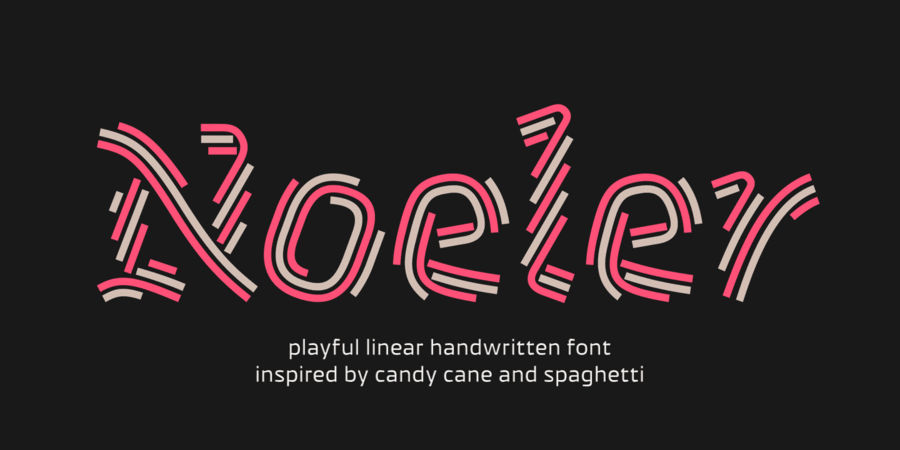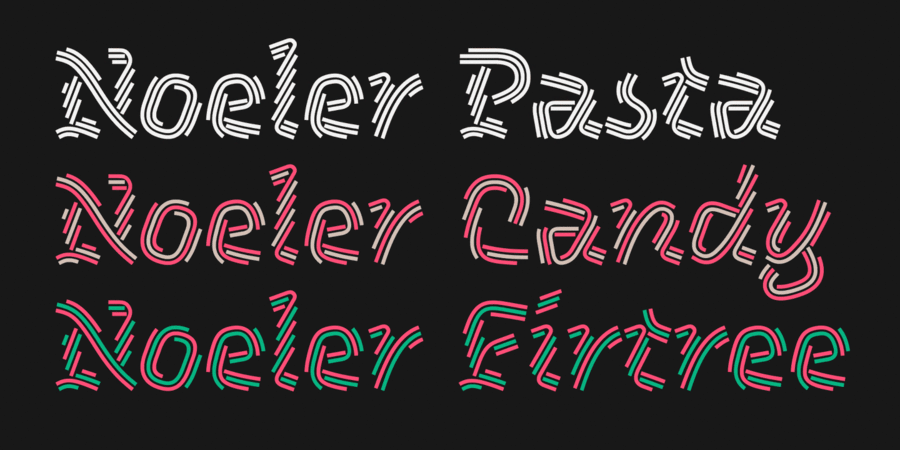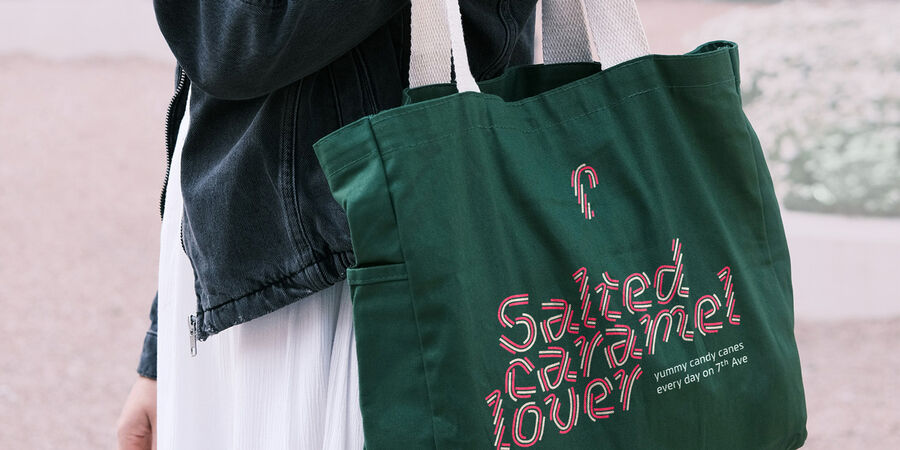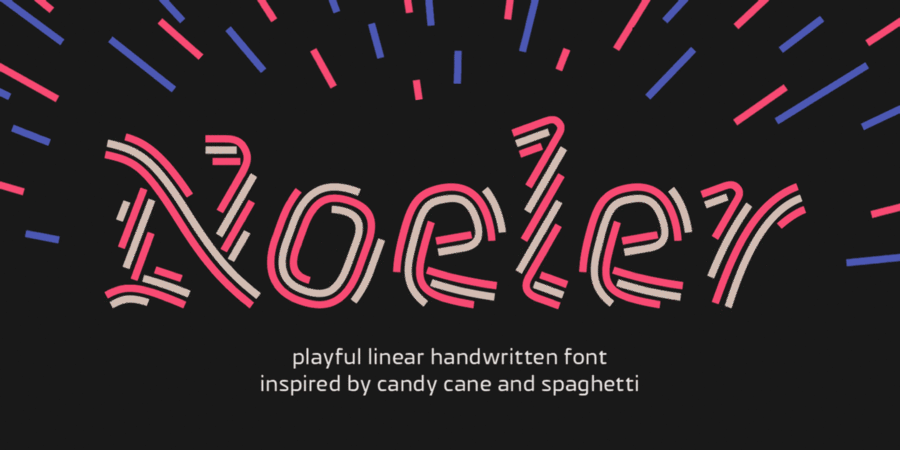
Noeler — грайливий лінійний рукописний шрифт зі святковим настроєм. Сімейство шрифтів включає один некольоровий шрифт (Pasta), натхненний формами спагетті, та два кольорові шрифти (Candy, Firtree), натхненні карамельною тростиною та різдвяними прикрасами.
Форма та колір. Історія цього шрифту починається з форми карамельної тростини, яка нагадала мені латинську велику літеру J, і так з'явилась ідея того, що ця закручена форма і ці кольори можуть бути літерами. Цікаво, що у не-кольоровому виконанні ті ж самі форми починають нагадувати спагетті, і саме тому стилі шрифтової родини отримали назву що відповідає їх візуальної функції. Отже, форма літер зібрана з щільно укладених одна до одної ліній, десь скручених в канат, а десь спрямованих паралельно. Виклик полягав у тому, щоб, навіть не маючи чіткого контуру, форма літер легко впізнавалась. Саме тому лінії розташовані доволі щільно, але не настільки щільно щоб кольори сусідніх ліній зливалися між собою. Лінії уникають гострих кутів на згинах, щоб підкреслити пластичність та м'якість форми, проте краї лінії не є заокругленими, тож форма, хоч і грайлива, але не виключно дитяча. Настрій та стиль. Бачення підказувало, що настрій шрифту має бути святковим, різдвяним, фестивальним. Коли ж ще смакувати карамельні тростини як не під час зимових свят! Тож рукописний стиль пасував якомога краще аніж сухий геометричний. Тут є і трішки асиметричних засічок в малих літерах, і трішки фрактури в великих літерах. Форма отримала декілька різних кутів нахилу, щоб підкреслити свою грайливість та відмову бути серйозною. Ні, пане, на свята ми не будемо серйозними. Ми будемо святкувати й веселитися! Стилі: Pasta, Candy, Firtree. Писемності: Латиниця, Кирилиця, Грецька. Мови: 500+ Кількість гліфів: 1452. Формат: OTF – OpenType з контурами PostScript. Кольорові шрифти: Noeler має два кольорові шрифти – Candy (рожевий + карамельний) та Firtree (рожевий + зелений). Кольорові шрифти представлені у двох версіях – з таблицею COLR або таблицею SVG. Версія COLR потрібна для всіх веб браузерів та більшості комп'ютерних програм. Версія SVG потрібна для InDesign, Photoshop, Illustrator, After Effects, Premiere Pro, Inkscape, CorelDRAW. Figma поки що не підтримує кольорові шрифти (перевірено у 2025 році). Стилістичний набір 2 “Decorations”: Шрифт містить набір із 50 примітивних лінійних декорацій, які можуть бути стартовою точкою натхнення для ваших різдвяних дизайнів. Набір включає наступні іконки: сніжинки, зірки, зірка Бетельгема, п'ятикутні зірки, серця, цукерки у формі тростини, ялинки, ялинові гілки, сніговик, пряниковий чоловічок, ялинкові шари. Деякі з них представлені в різних розмірах та вигляді, щоб пасувати до малих та великих літер. Є два способи застосування декорацій: 1. Відкрийте панель «Гліфи» в графічному редакторі та виберіть декоративний елемент вручну. 2. Активуйте стилістичний набір 2 та введіть у текст кодові слова від :decoration1: до :decoration50:. Стилістичні альтернативи: Y f s. Контекстні альтернативи: Дд Дз Ду Цд Цз Цу Щд Щз Щу цд цз цу щд щз щу. Лігатури: Th fb fh fk fl ff ffb ffh ffk ffl ЇЇ ії її. Цифри: Лінійні (за замовчуванням), старого стилю, Superscript, Subscript, Numerator, Denominator. Шрифт розробив Михайло Рафайлик у 2025 році. Світ ловив мене, та не спіймав!